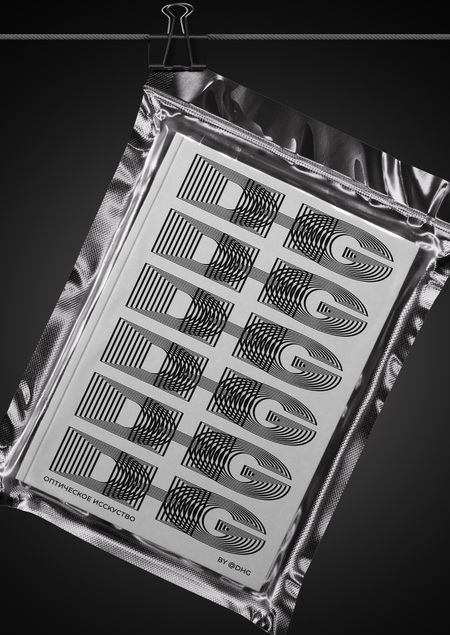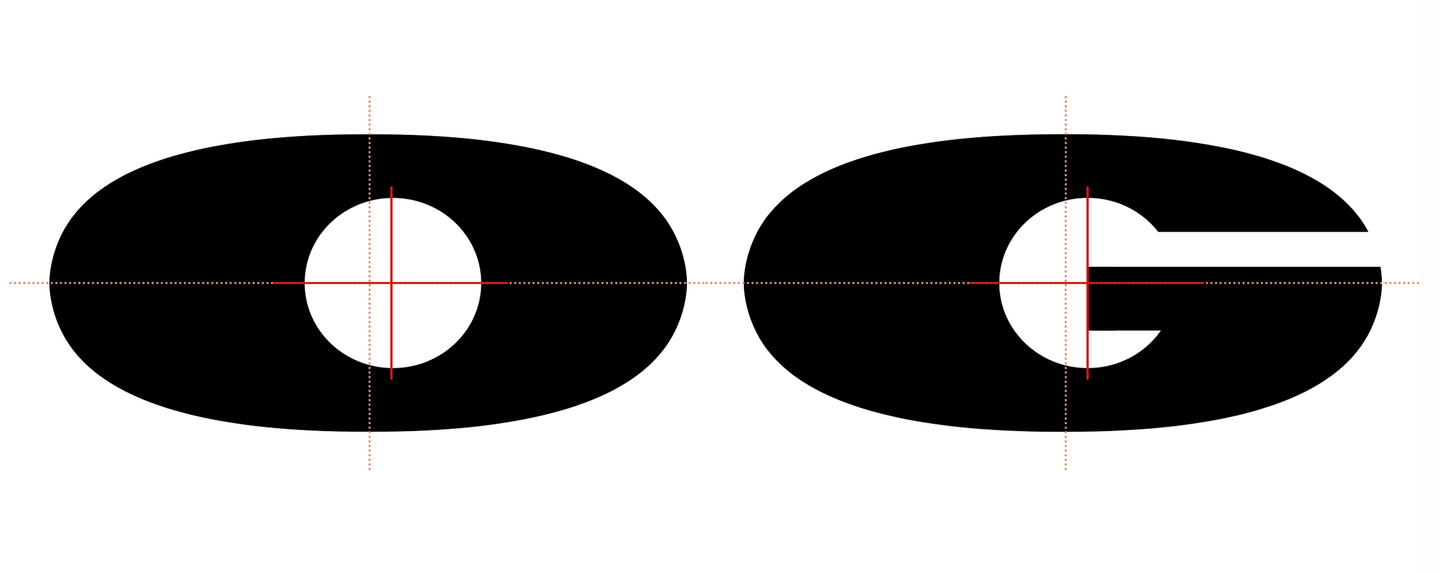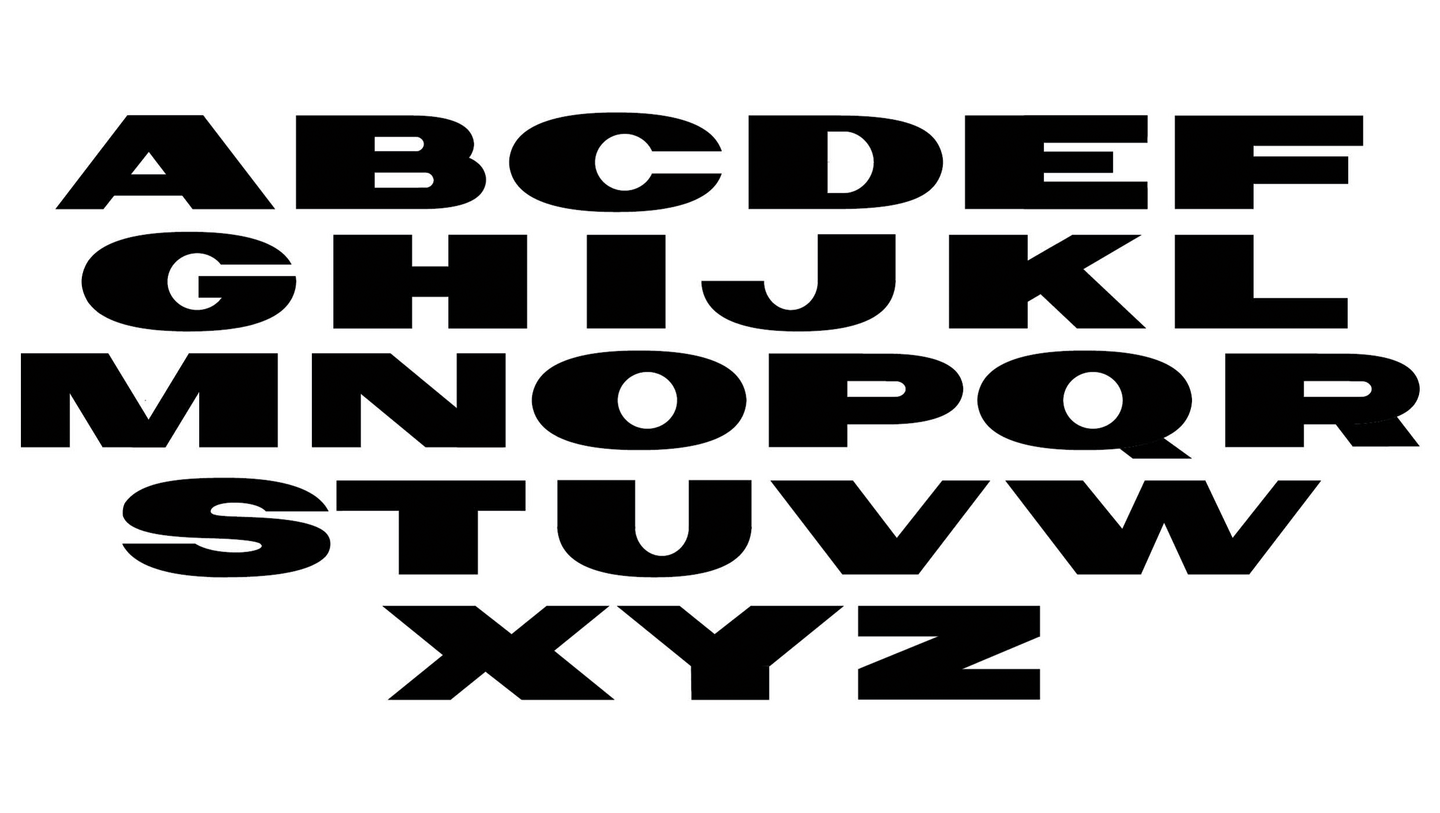
Шрифт СHAMELEON
Шрифт СHAMELEON — это типографский муар. Крупные кегли раскрывают его сложный декоративный характер, а мелкие — сохраняют функциональность и читаемость. Шрифт становится главным активом, способным к трансформации.
Основа
Ключевые параметры: • Гротеск • Простая основа необходима как «холст» для наложения сложного декоративного элемента • Extended • Bold